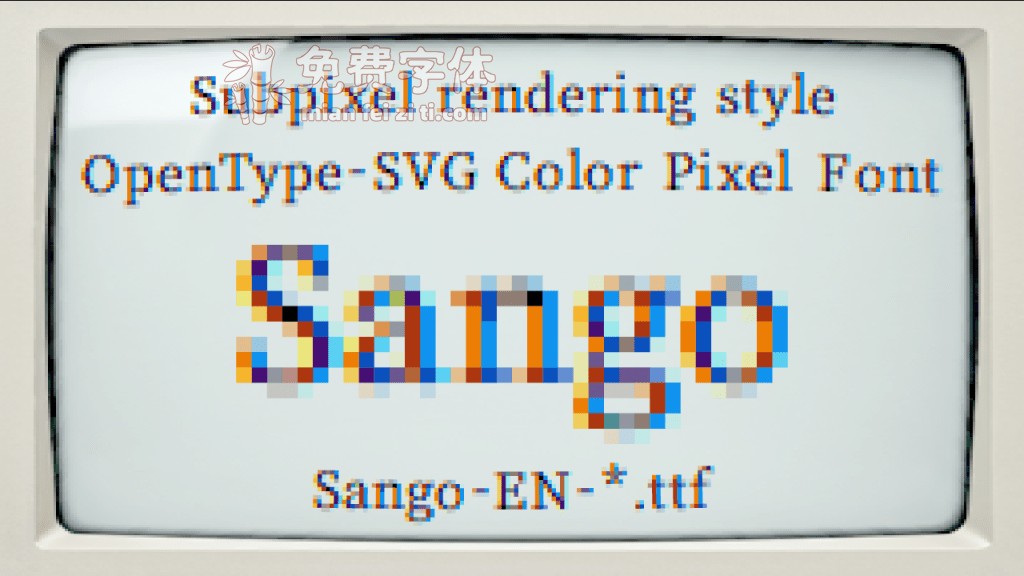
珊瑚是一种参考显示器的子像素渲染而设计的彩色字体。 此字体使用一种称为“像素字体”的样式,该样式由方点组成。 像素字体是一种设计,其中小方点聚集在一起形成字母。 它在表达复古游戏和强调数字感的艺术时特别受欢迎。
珊瑚的一个主要特点是向每个像素添加了颜色信息。 这进一步强调了许多像素字体在数字和模拟之间的中间表示,并且看起来有点模糊,甚至感觉像一组随机的点,具体取决于视角和大小。
顺便说一句,在“珊瑚”中,透明度是在颜色部分设置的,因此如果是浅色背景,则不太可能导致轮廓在放置时浮动的不自然状态(所谓的边缘)。 (但请注意,由于它最初是基于黑色文本创建的,因此将其放在深色背景上可能会导致颜色下沉,无法按预期显示。 在这种情况下,如果可能,可以通过在应用程序端反转颜色来改进它。 )
“珊瑚” 是一种独特的彩色字体,它会根据它的使用和排列方式而大大改变印象。 我希望你喜欢各种设计!